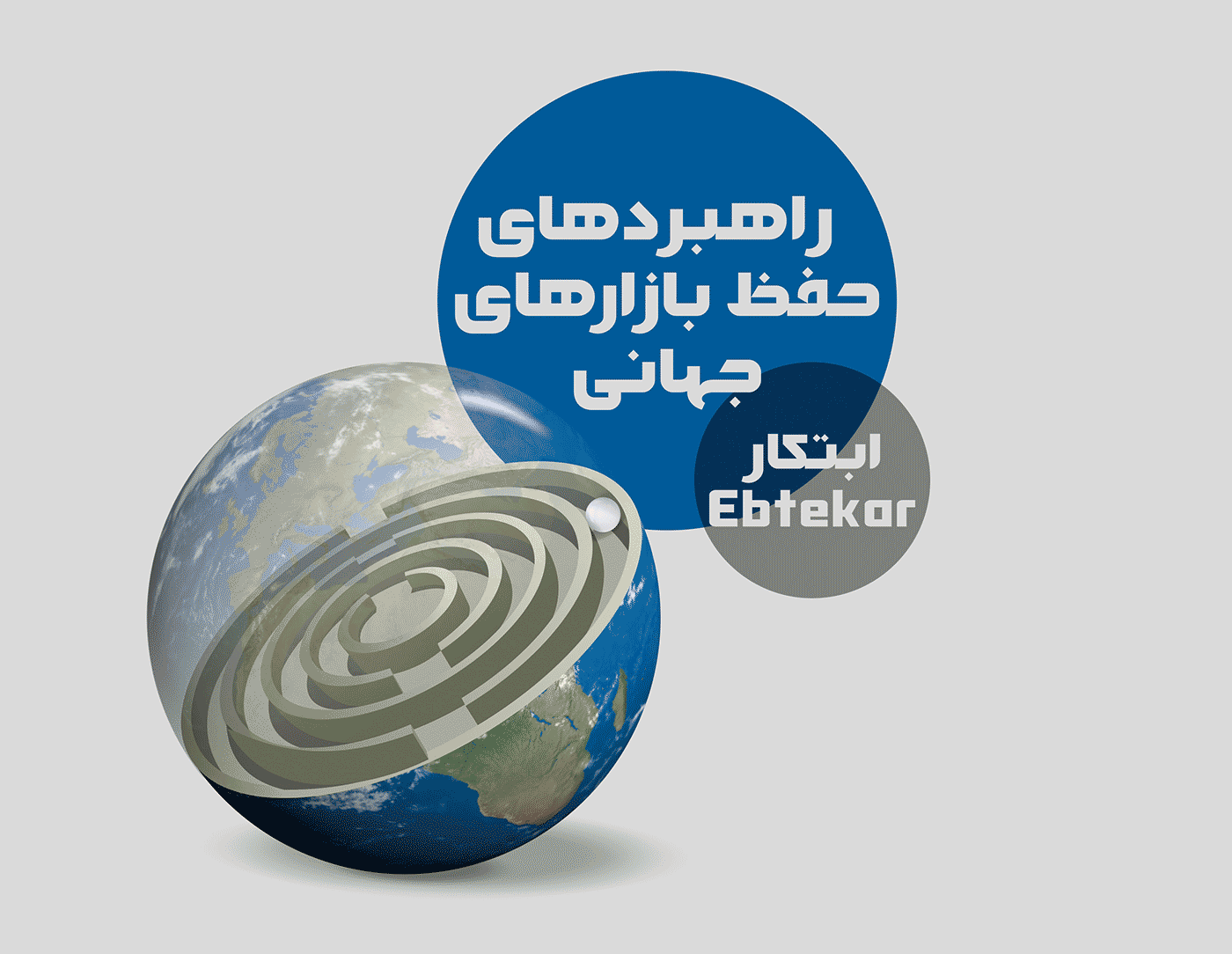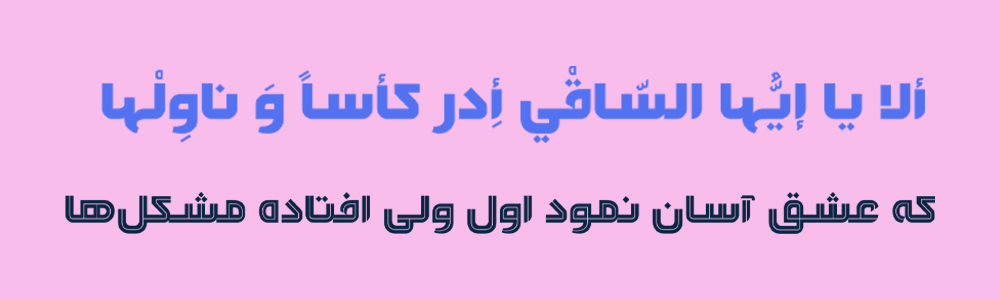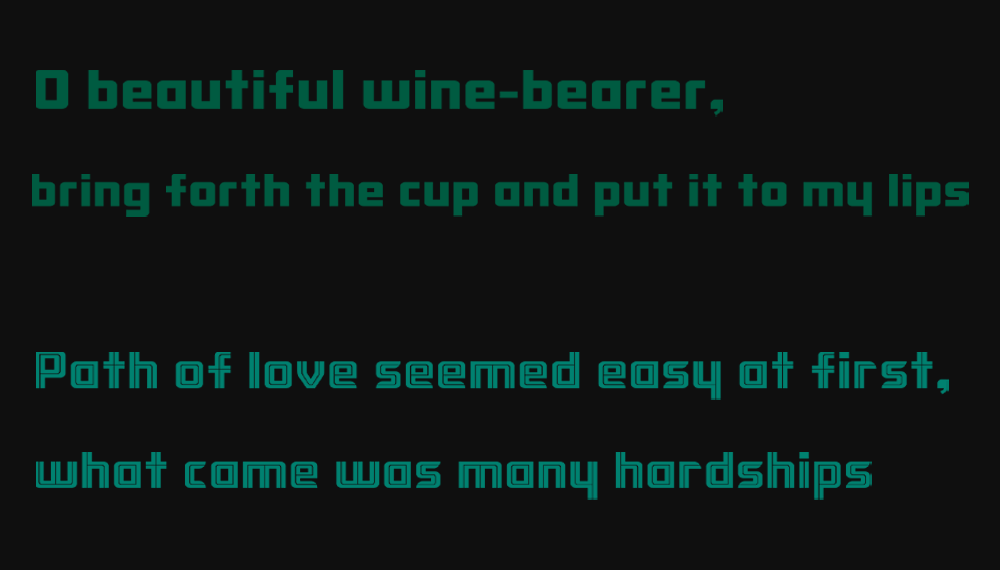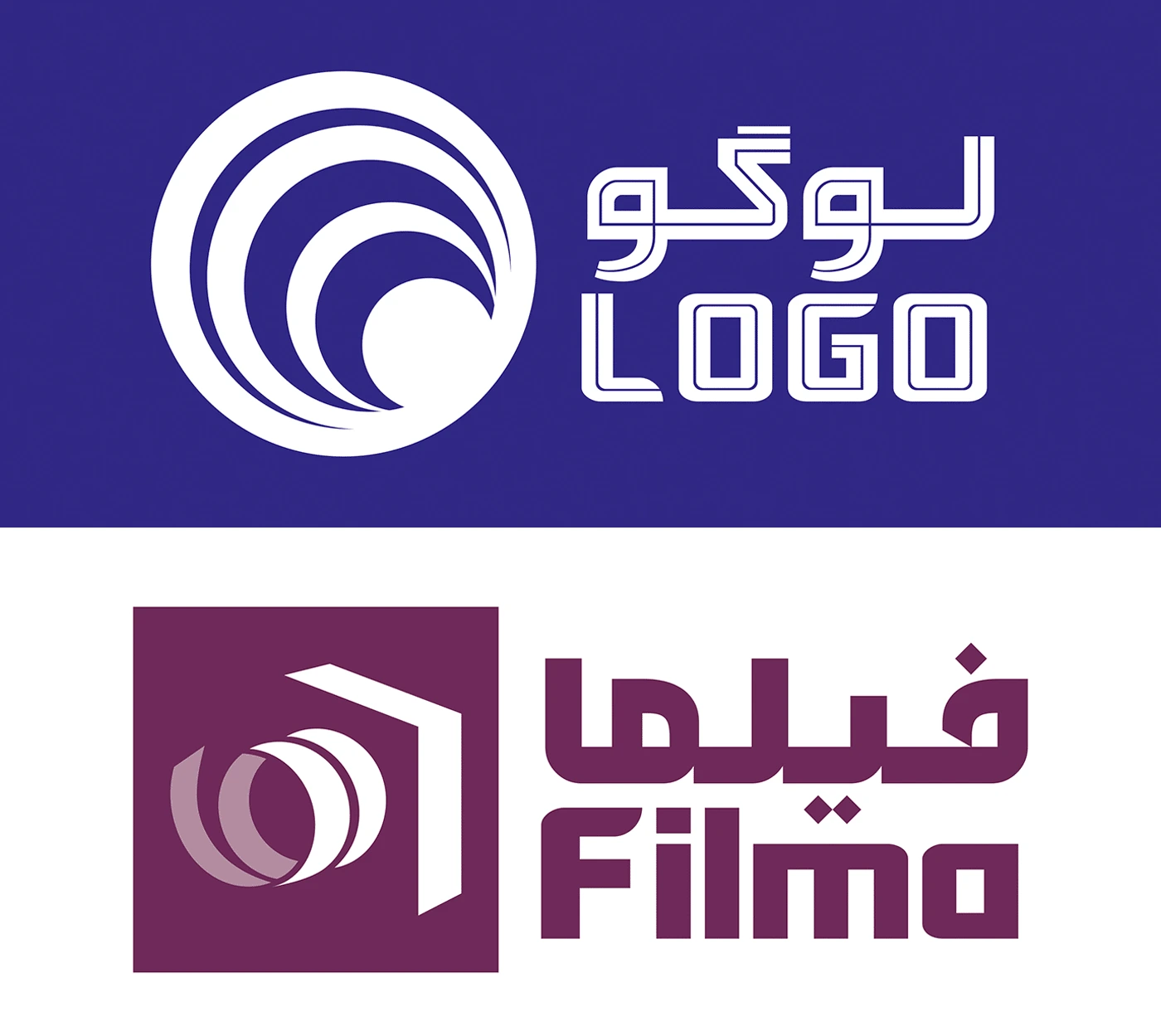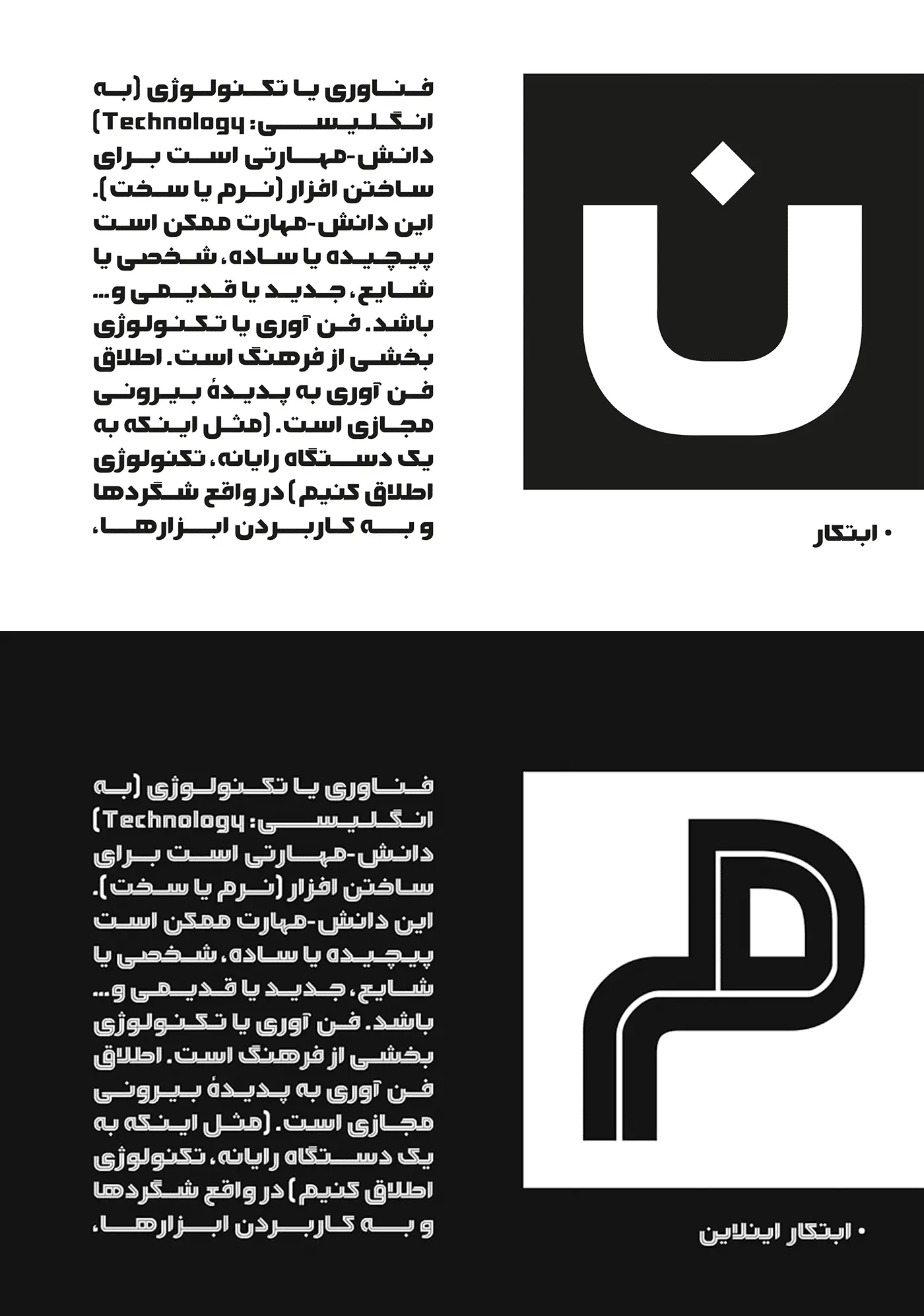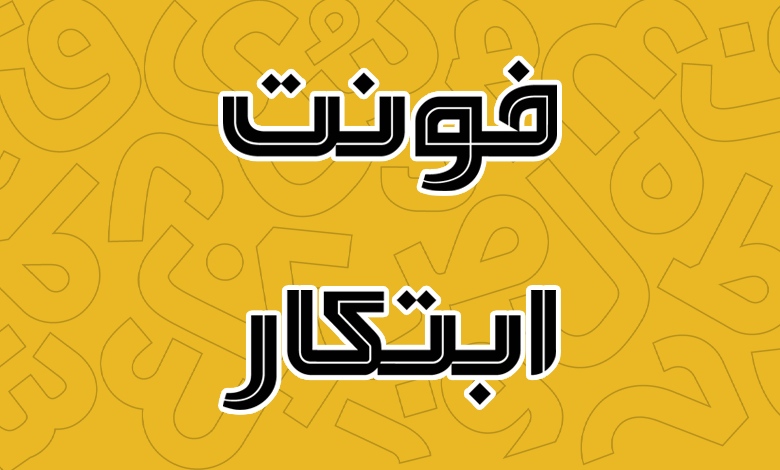
فونت ابتکار (Ebtekar)
فونت ابتکار (به انگلیسی: Ebtekar) قلمی در گروه فونتهای هندسی و مناسب برای عناوین، تبلیغات و متنهای کوتاه است که در دو سبک معمولی و اینلاین طراحی شده است. این قلم جزو معدود فونتهای بینالمللی فارسی است که در ابتدا در سایت فونتبراس آمریکایی به صورت بینالمللی عرضه میشده است.
طراحی این فونت بر اساس ساختار هندسی حروف صورت گرفته که در تمامی زبانها، از این سبک استفاده شده است. این قلم توسط آرمان خرمک طراحی شده است و در نخستین سالانه هنر طراحی کتاب در سال ۹۴ شایسته تقدیر شناخته شد.
در ادامه این نوشته از سایت فونتچی به نقد و بررسی کامل فونت ابتکار میپردازیم؛ قلمی نمایشی با ساختار بینالمللی که برخلاف سایر قلمهای فارسی، از زبان پشتو نیز پشتیبانی میکند.
قلم ابتکار مشابه دو قلم دیگر نظیر فونت یکتا و فونت همتا علاوه بر ساختاری معمولی که دارد، از یک سبک اینلاین هم پشتیبانی میکند.
از این فونت میتوانید برای طراحی جلد کتاب گرفته تا ساخت لوگو تایپ، عناوین، تبلیغات و بستهبندی روی محصولات استفاده کنید.
فونت ابتکار در دو ساختار وزنی و اینلاین
فونت ابتکار از دو سبک پشتیبانی میکند. این فونت در هر دو سبک از وزن متوسط Medium پشتیبانی میکند که برای استفاده در محیطهای تبلیغاتی کاملا مناسب هستند.
ساختار وزنی قلم طوریاست که هر چه ابعاد فونت بزرگتر شود، خوانایی بهتری خواهد داشت. خصوصا در وزن اینلاین که خطوط جدا کننده در حروف بهتر دیده میشوند. چنین طرحی را پیش از این در فونت پرنیان مشاهده کردیم که در آن از گلدوزی برای طراحی حروف الهام گرفته شده بود و هر چه حروف بزرگتر میشدند، خطوط هاشور خورده بهتر دیده میشد.
قلم ابتکار در این وزنها دارای دو سبک است؛ سبک اول که ساختاری معمولی مشابه هر فونت دیگر دارد. دندانهها و شکل حروف دارای ظاهری سخت و رسمی هستند. سبک دیگر این قلم نیز خطی اینلاین است که حروف را بهصورت سراسری به دو بخش تقسیم کرده است. در هر دو این سبکها شاهد دو حالت مختلف هستیم که بهسختی میتوان تفاوت بین انها را متوجه شد.
پشتیبانی از ۵ زبان مختلف
فونت فارسی ابتکار یک قلم خانوادهدار بینالمللی است. این قلم جدای از زبان فارسی، از زبانهای عربی، اردو، انگلیسی و پشتو نیز پشتیبانی میکند و در تمامی ساختار این زبانها، چه برای زبانهای با رسم خط فارسی و چه لاتین، سبک تمامی حروف یکسان و دارای طراحی اختصاصی است.
در زبان عربی و سایر زبانهای مبتنی بر رسم خط فارسی، پشتیبانی استانداردی دارد. طوری که تمامی حروف به صورت یکسان طراحی شده و هر جا هم که دو زبان دارای حروف متفاوت بوده یا تغییراتی جزئی دارند، مختص استفاده برای آن زبان پیاده سازی شده است. از جمله این موارد میتوان به حروف «ک، ی، ه، ؤ، ئ» در زبان عربی اشاره کرد.
علاوه بر حروف، اعراب هر زبان، گلیفهای نمایشی تزئینی در زبان اردو و همچنین اعداد نیز به طور کاملا استاندارد بر اساس هر زبان طراحی شده است. یا در زبان اردو که حروف «ه، ی» در میانه یا انتهای حروف ظاهری متفاوت دارند.
فونت ابتکار انگلیسی دارای استاندارد بین المللی است. یعنی برای زبان لاتین محدود به زبان انگلیسی نبوده و سایر زبانها مثل ترکی استانبولی یا فرانسوی که بر اساس رسم خط لاتین بوده و صرفا برخی حروف دارای شکل ظاهری متفاوتی (دارای نقطه یا عرض متغیر) هستند، نیز پشتیبانی میکند.
مناسب برای طراحی لوگو تایپ چندگانه
یکی از ویژگیهای منحصر بهفرد این قلم، امکان استفاده از آن برای طراحی لوگوتایپ است. بر خلاف سایر قلمهایی همچون فونت مربع، فونت رخ، فونت والمان و سایر قلمها از این فونت میتوان برای طراحی لوگوی چندگانه استفاده کرد.
منظور از لوگوی چندگانه این است که لوگویی بتوانید با این قلم طراحی کنید که هم برای زبانهای بر اساس رسمخط فارسی و هم برای زبانهای لاتین دارای استایل یکسانی خواهد بود.
پشتیبانی کامل از اعداد فارسی، عربی و لاتین
در زبان عربی که دارای ساختار متفاوتی برای تایپ اعداد «۴۵۶» نسبت به اعداد «۴۵۶» فارسی است، استانداردها رعایت شده است.
این قلم برای اعداد لاتین انگلیسی هم همان ساختار را دارد و با همان دو سبک معمولی و اینلاین اعداد نیز برای این زبان دارای طراحی اختصاصی خود هستند.
دو فرمت WOFF و WOFF2 ابتکار برای استفاده در وبسایت مناسب هستند. با توجه به اینکه این قلم برای عناوین کوتاه مناسب است، با نصب آن در سایت میتوانید در بخشهایی مثل عناوین نوشتهها، تیترها، نقل قول، باکسهای رنگی و موارد دیگری نظیر اسلایدر و بنرهای سایت استفاده کنید تا توجه بیننده را به خود جلب نماید.
ساختار ضخیم و اینلاین این فونت طوری است که با قرارگیری در کنار یک فونت متن دیگر میتواند جلب توجه بیشتر را به دنبال داشته باشد. خصوصا در بخشهایی مثل عناوین که سبب کلیک کاربر و رفتن به صفحات متعدد در یک سایت خواهد شد.
مزیت دیگر این قلم از این نظر، کمک به بهبود رابط کاربری سایت است که کاربر هم در بین متنهای طولانی گم نخواهد شد. چنین ساختار فونتی، خصوصا در موبایل به کاربر کمک میکند تا محتوایی که به دنبال آن است را در یک ارتباط چشمی سریع، بهتر پیدا کند.